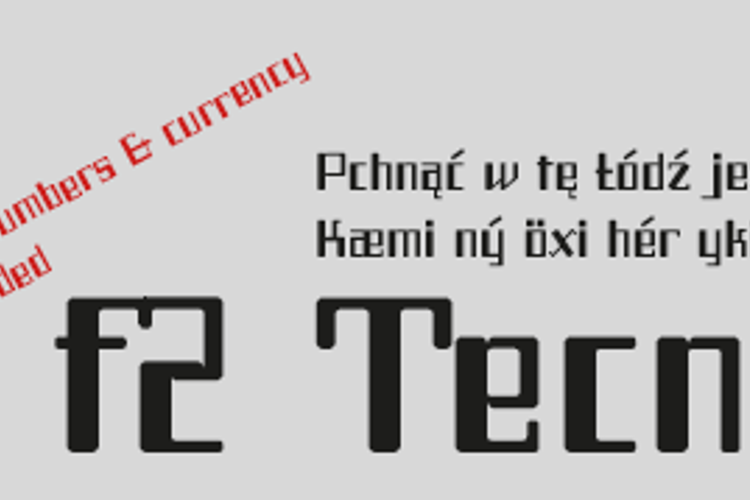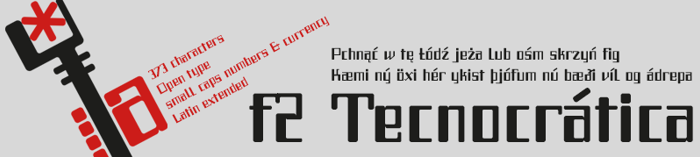
f2 Tecnocratica Font
Tipografía sans con contraste, display, geométrica, industrial con acabado redondeado y proporciones áureas en todos los elementos de las letras, alturas, anchuras, angulos, astas, metrics, etc. he definido estos elementos usando números de Perrin y cifras de las sucesiones de Fibonacci y Lucas.
Sans contrast, display, geometric, industrial and rounded finish with golden proportions in all elements of the letters, heights, widths, angles, antlers, metrics, etc.. I have defined these elements using Perrin numbers, Fibonacci and Lucas sequences.